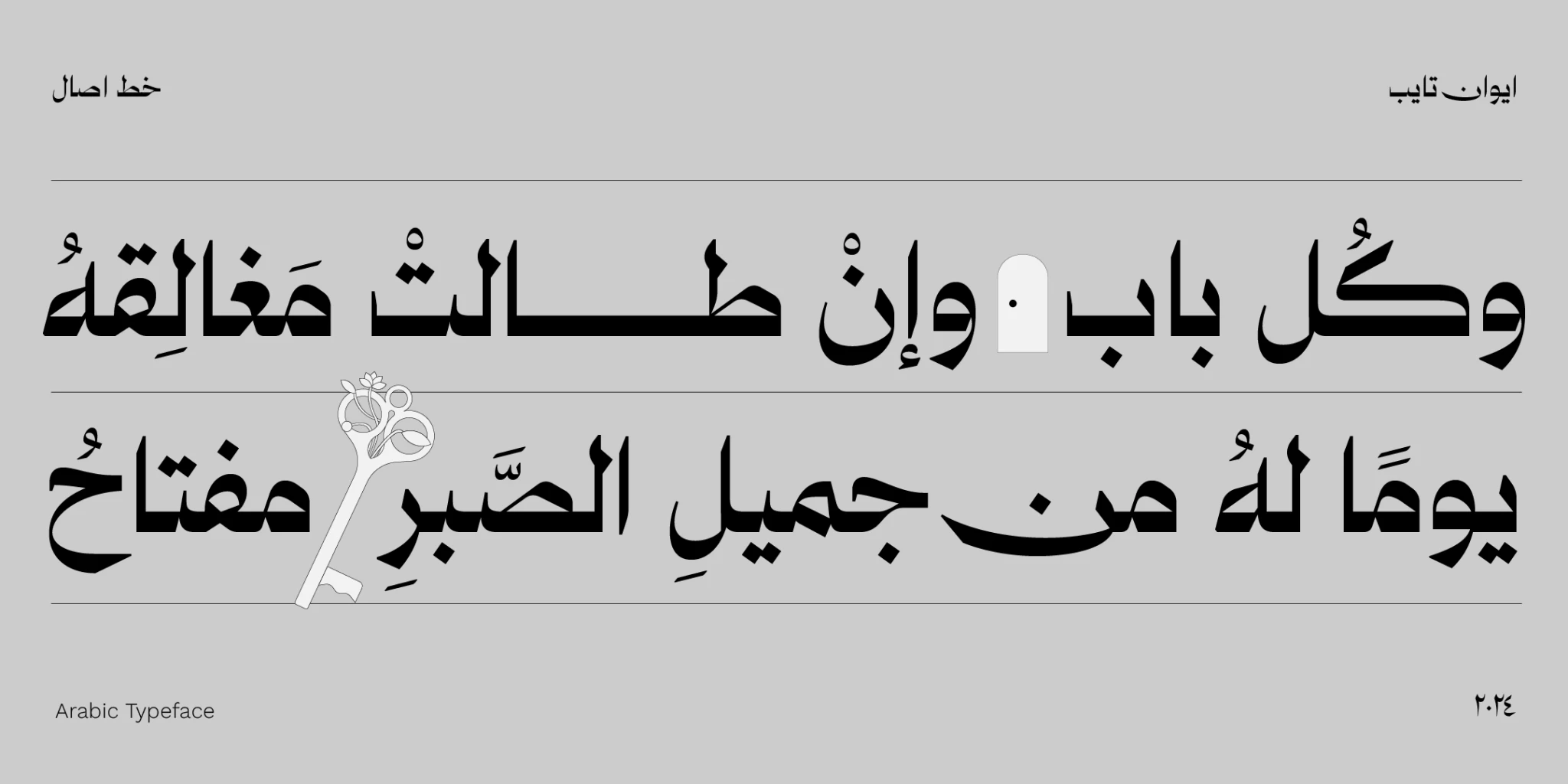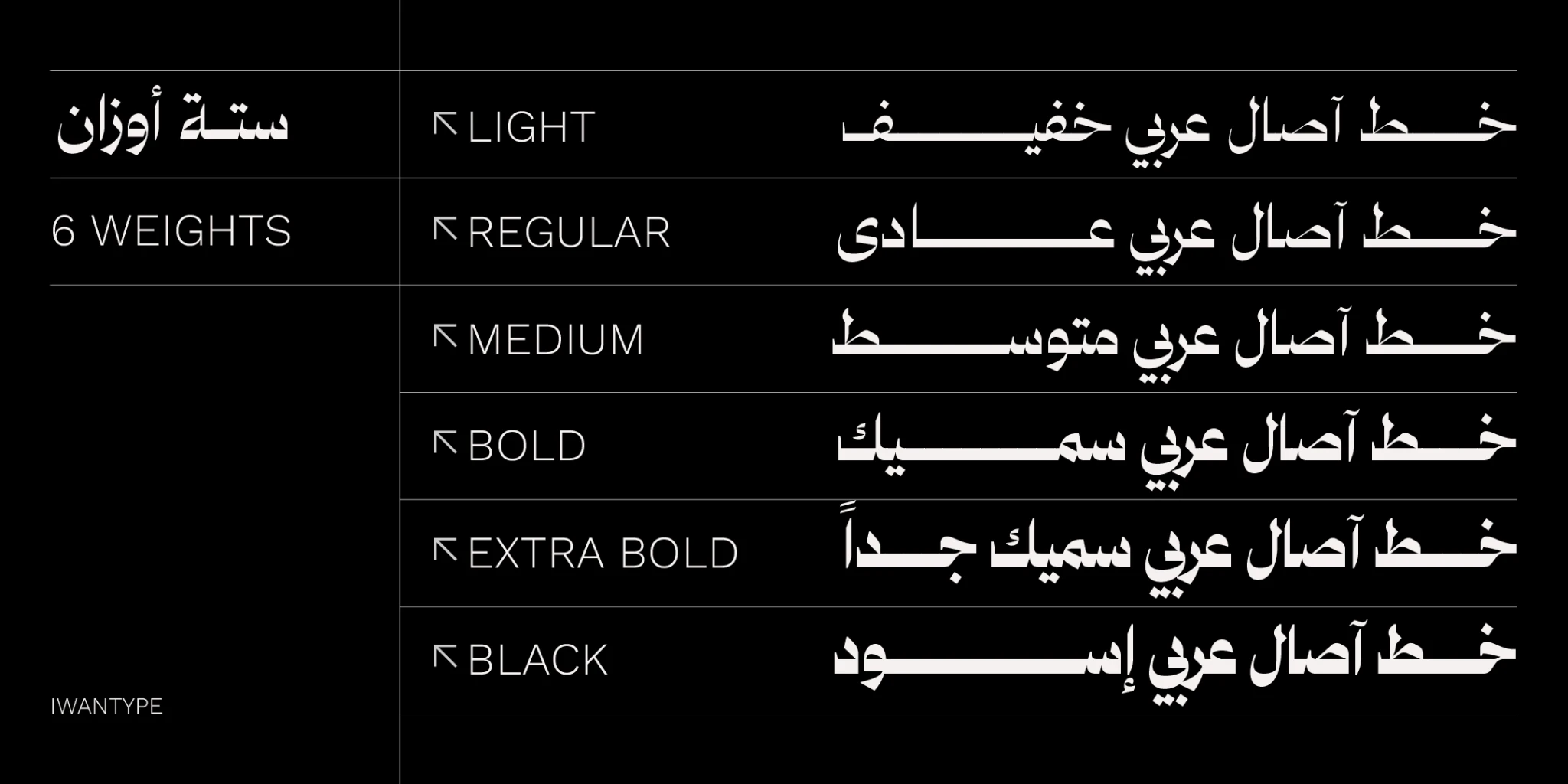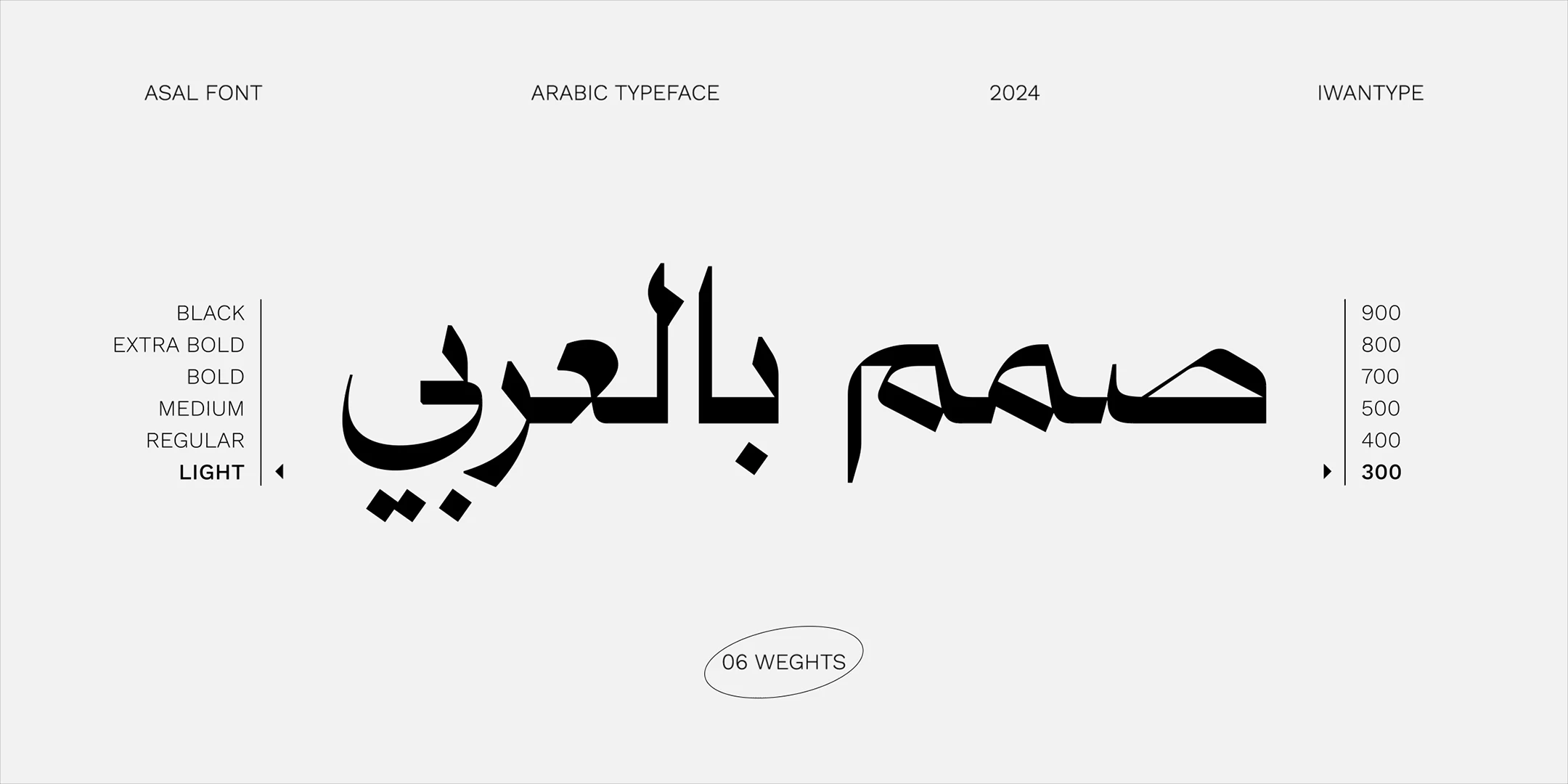
أصال هو خط طباعي عربي يجمع بين التقليد والحداثة بأناقة فريدة. يتميز بتصميمه الأنيق واستخدامه للخطوط الهندسية، مما يضفي عليه طابعًا مميزًا وجذابًا. يتضمن ميزات أوبن تايب مثل الحروف البديلة والحروف المركبة، مما يتيح للمستخدمين تجربة متميزة في التصميم العربي.